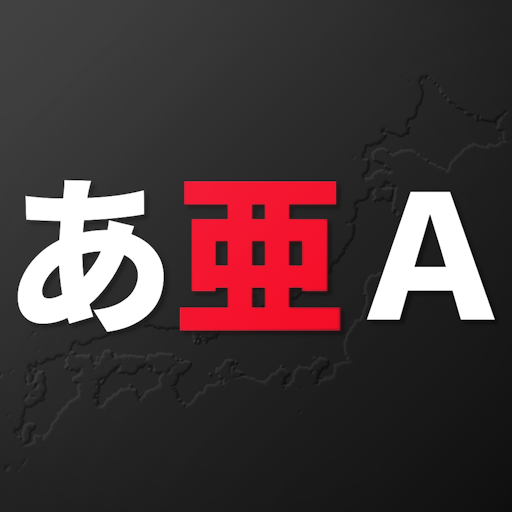
Japanese Map Fonts Sans
新しい日本語用マップフォントです。 変更されるのはマップ上の国名などのフォントのみです。 (VP名やGUI上のテキストなどは変更されません)
公式日本語対応以前のマップフォントのスタイルを参考にしつつ、漢字を主体に19295字のフォント追加を行いました。 また、フォントの解像度に余裕を持たせ、ロシア国家などの国名のジャギーが少なくなるようになっています。